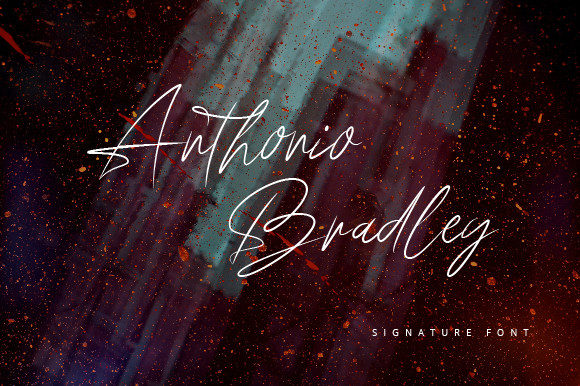
Creativefabrica Anthonio Bradley Font
[Creativefabrica] Anthonio Bradley Font
Энтонио Брэдли - тонкий и изысканный шрифт.
Он имеет стильный, элегантный и современный вид, который может быть использован для логотипов, брендинга, приглашений, канцелярских принадлежностей, свадебных конструкций, сообщений в социальных сетях, и многое другое!